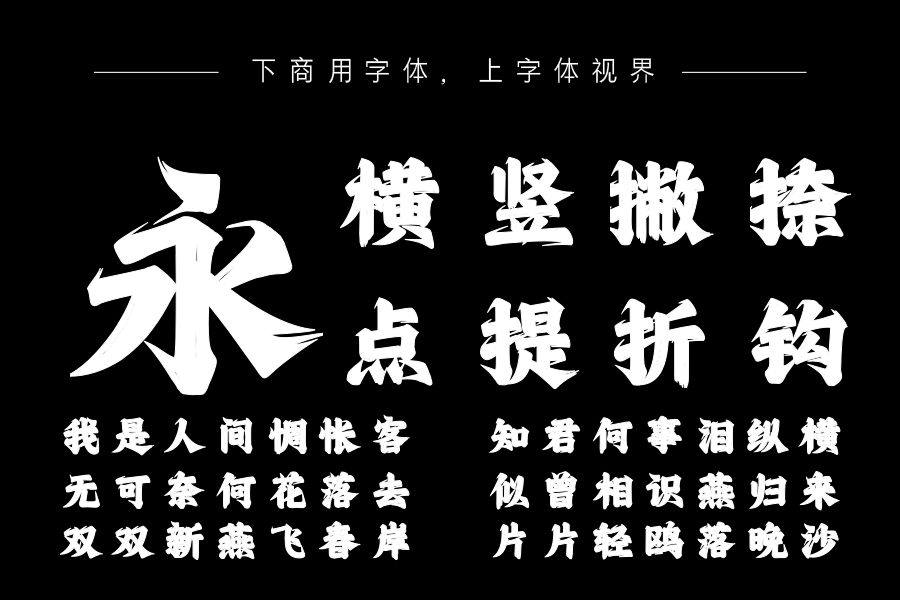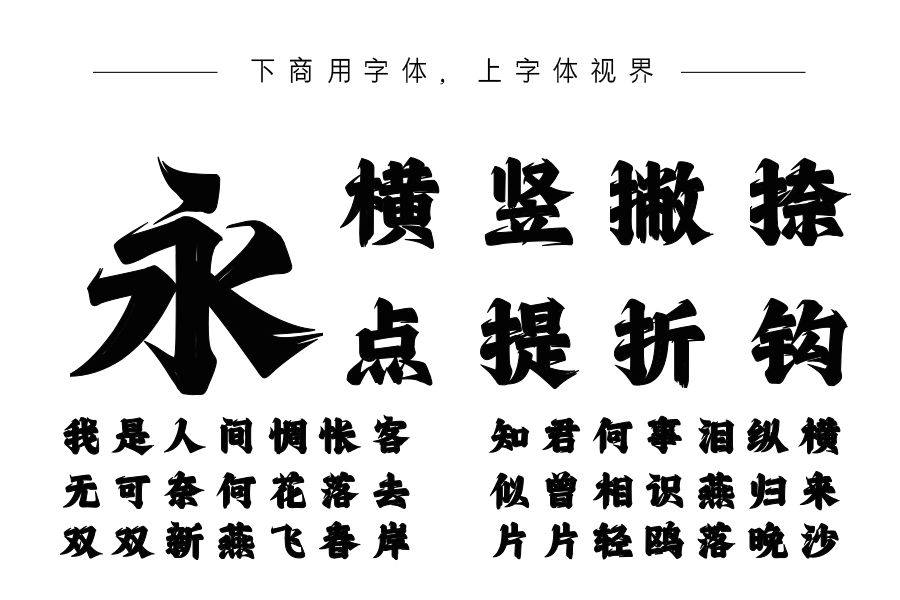
上首潇洒体,该字体具有书法特性,其笔画苍劲有力,横竖撇捺皆有风骨,流露出一种无拘无束、潇洒肆意的气息。适用于搭配标志、广告标语、商业广告等高端属性。购买须知:“下载服务费”与“字体VIP”所获得字体 仅用于个人非商用, 商用请联系付费授权。本字体为电脑用字,手机没有root权限不支持直接手机换字(手机如何root,请自行百度搜索教程)。购买前请先 了解清楚后再付款 ,字体为虚拟产品无法回收 一旦购买不支持退款。